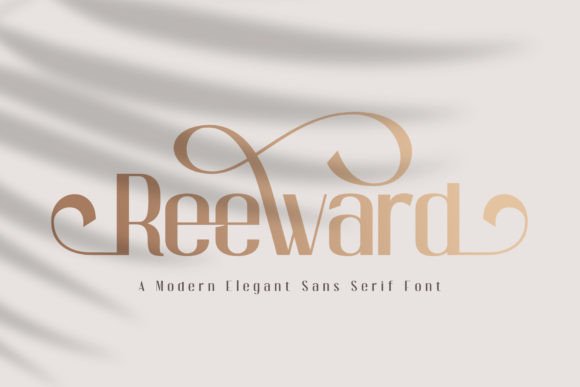
Reeward
適切なデザイン要素を見つけるのは難しい場合がありますが、Reewardは作品を即座に引き立てる優れたコレクションを提供します。
精密に作られたReewardは、クリーンなベクター、滑らかなタイポグラフィ、そして安心のための商用ライセンスを提供します。
POD(オンデマンド印刷)製品、結婚式の招待状、またはソーシャルメディアのグラフィックを作成している場合でも、Reewardは理想的です。